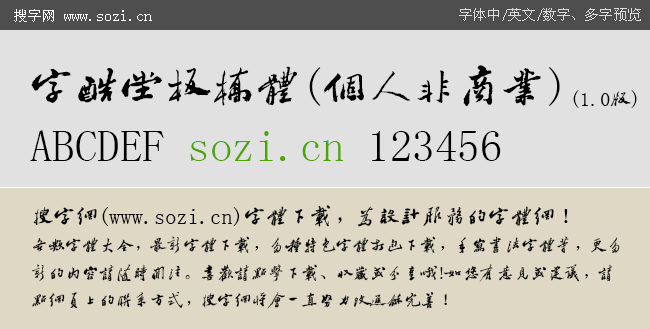
字酷堂板橋體(個(gè)人非商業(yè))
搜字網(wǎng)提供一款字酷堂板橋體(個(gè)人非商業(yè))中文書法字體下載字酷堂黃楷字體是一款以古代名人鄭板橋書法制作的字體,形體端秀而骨架勁挺,適合應(yīng)用于廣告設(shè)計(jì)、名片設(shè)計(jì)、包裝印刷、海報(bào)設(shè)計(jì)等應(yīng)用。